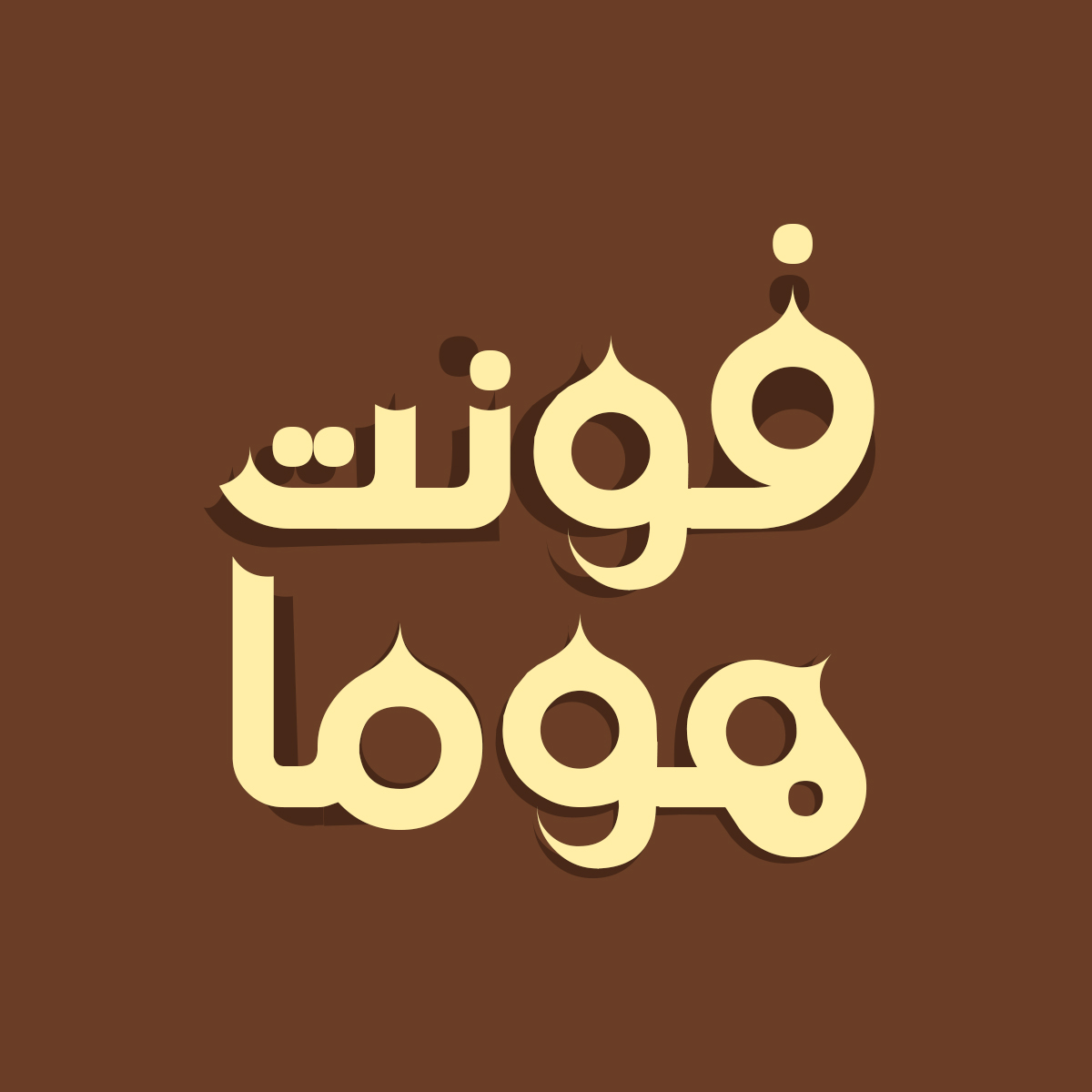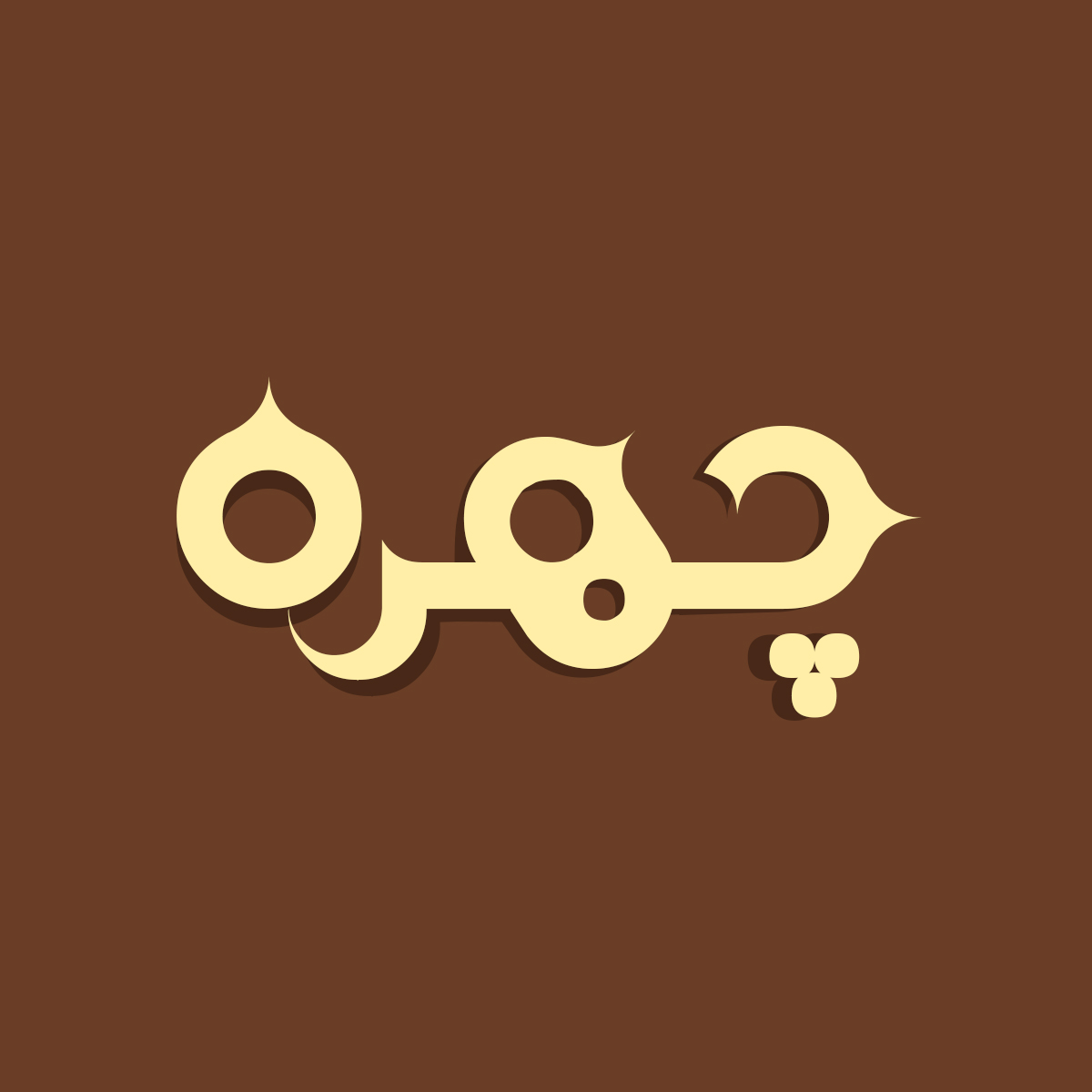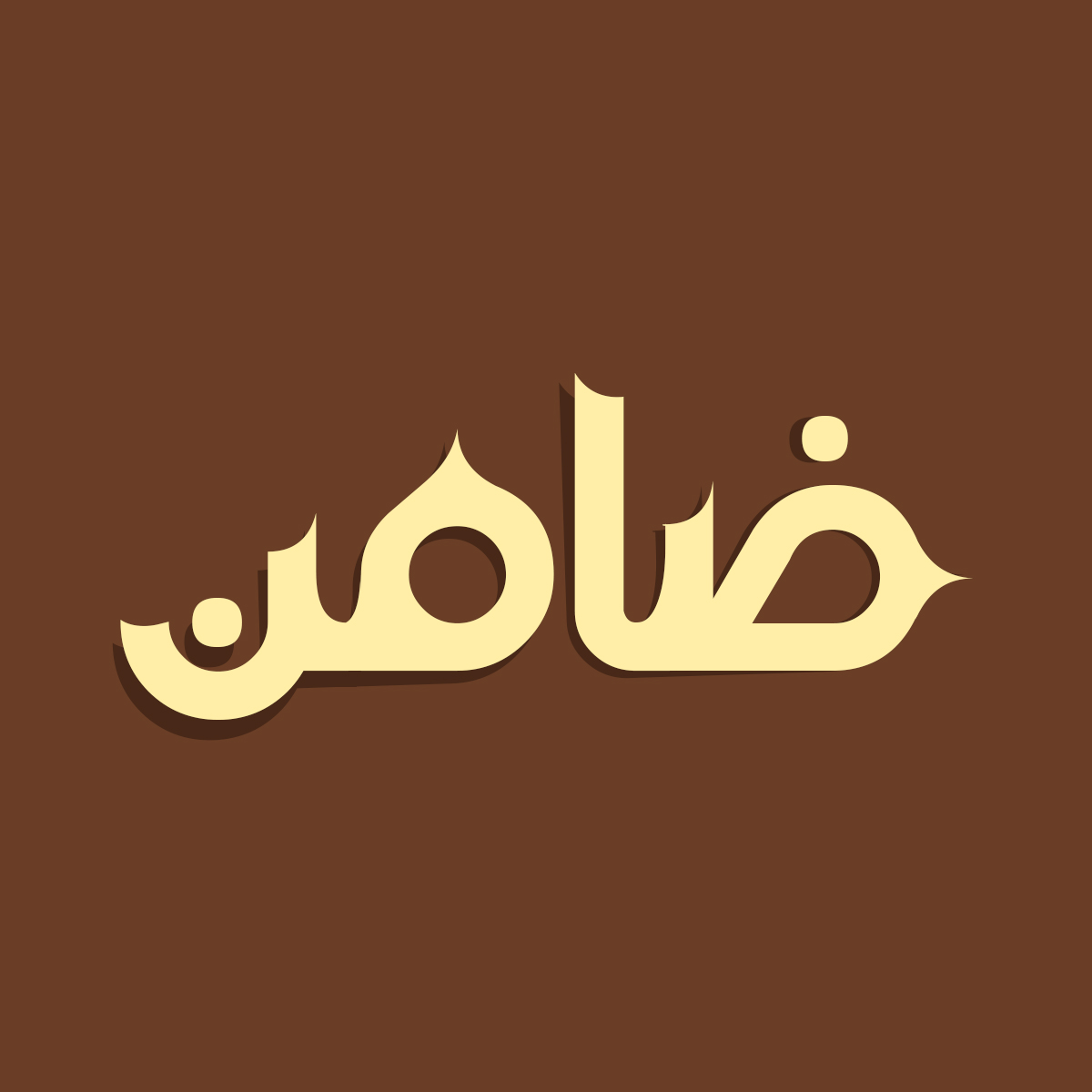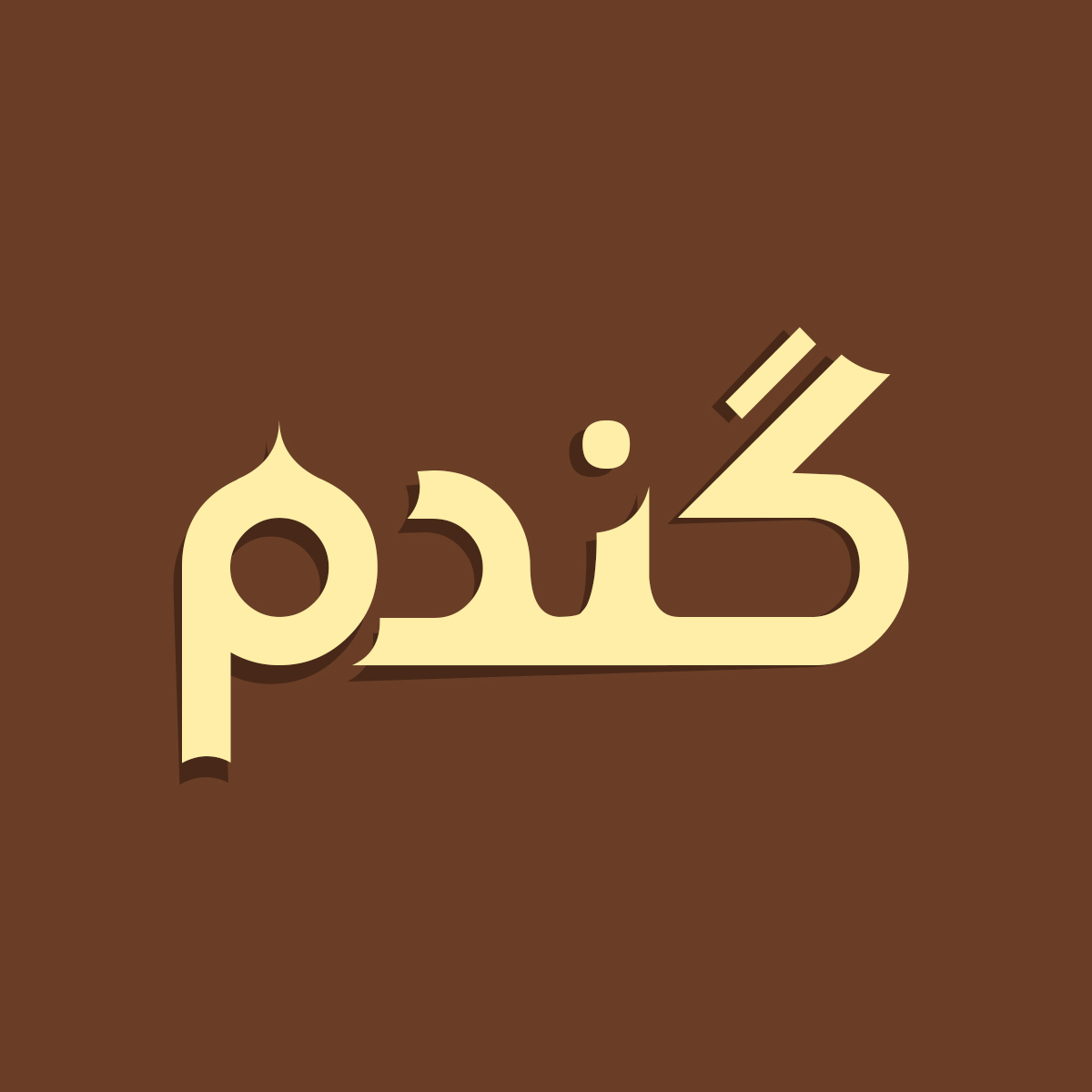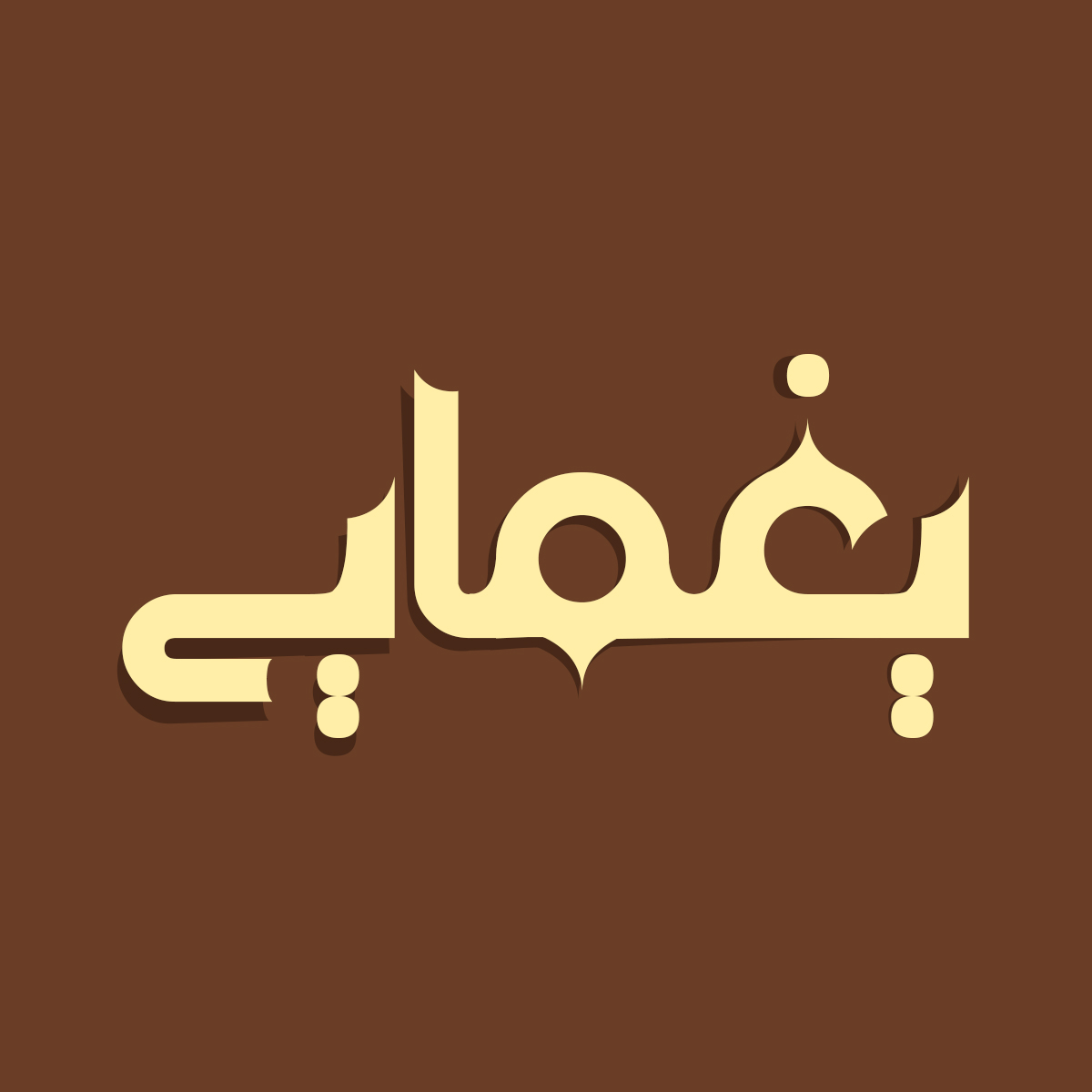
فونت فارسی هوما یکی از فونتهای خاص و متفاوت است که با طراحی منحصر به فرد خود میتواند به پروژههای شما جلوهای تازه و حرفهای ببخشد. فونت هوما با الهام از سبکهای مدرن و هندسی طراحی شده و حس خلاقیت و نوآوری را منتقل میکند. از این فونت در طراحی لوگوتایپ و تابلوهای چلنیوم به دلیل ساختار منحصر به فردش میتوانید استفاده کنید. در ادامه برای شما نمونه تایپهای این محصول حرفهای رو آماده کردهایم که میتوانید مشاهده کنید.
پیشنمایش و نمونه تایپ های فونت هوما